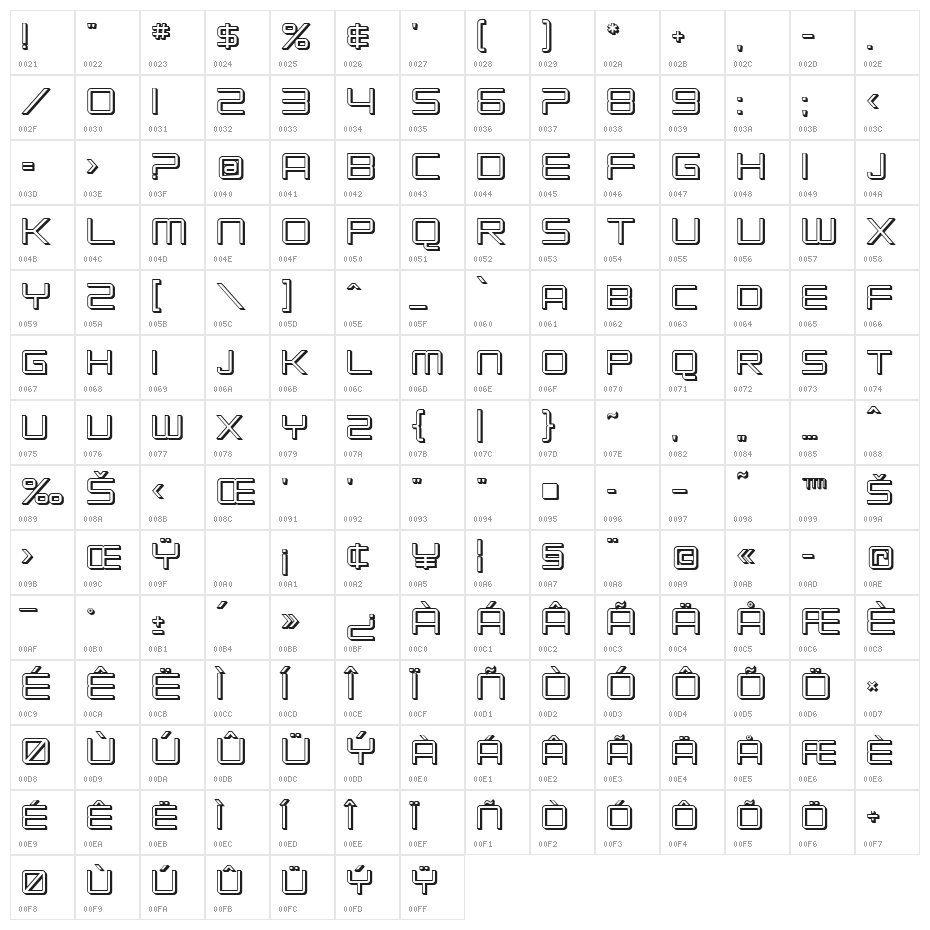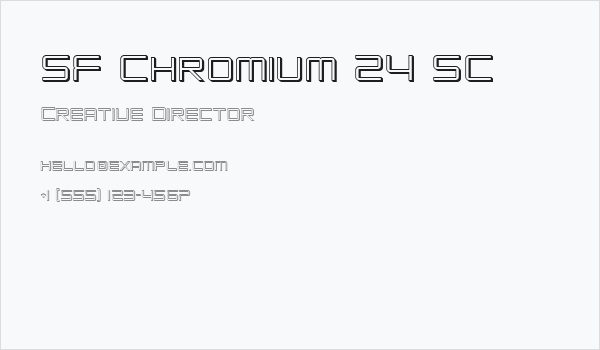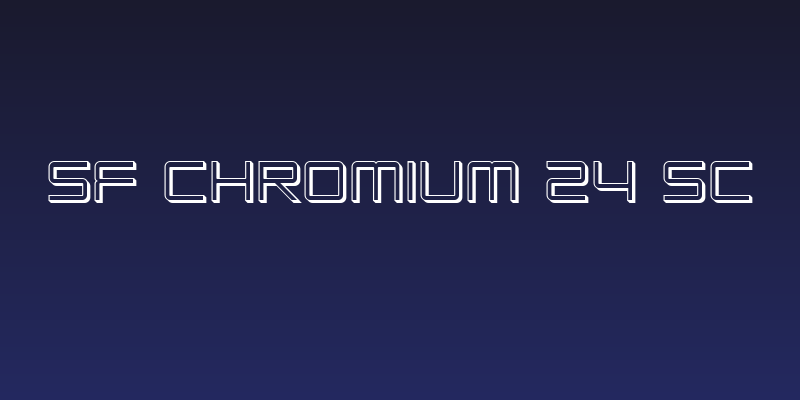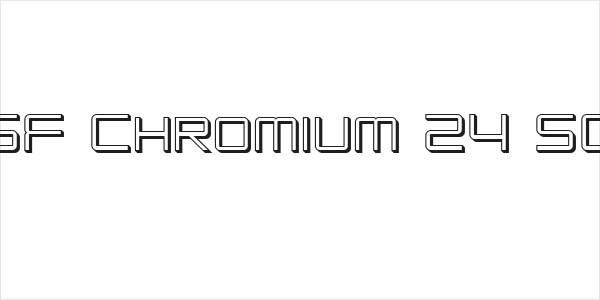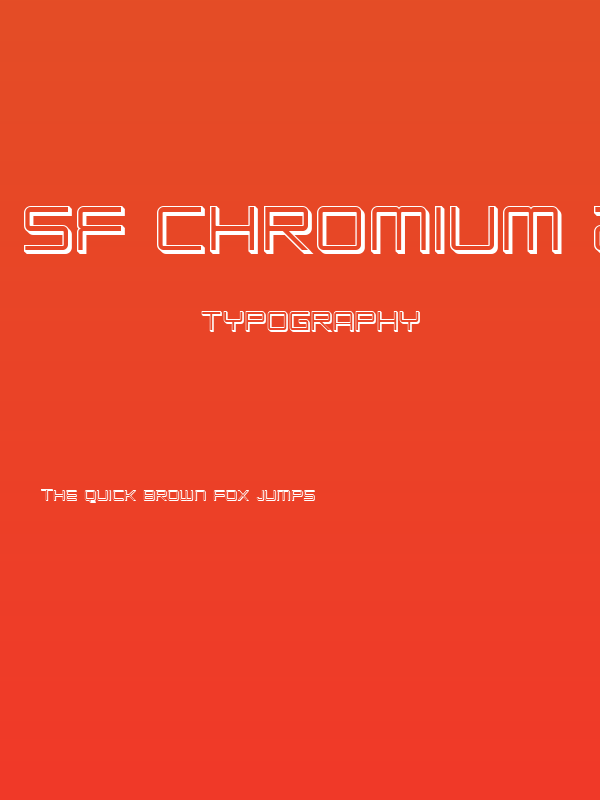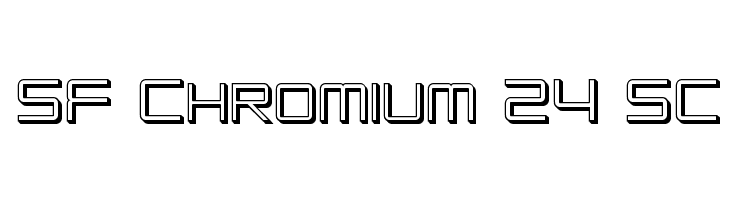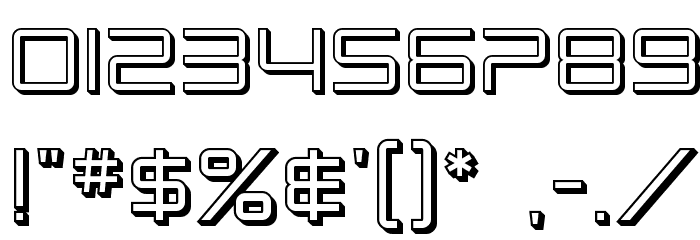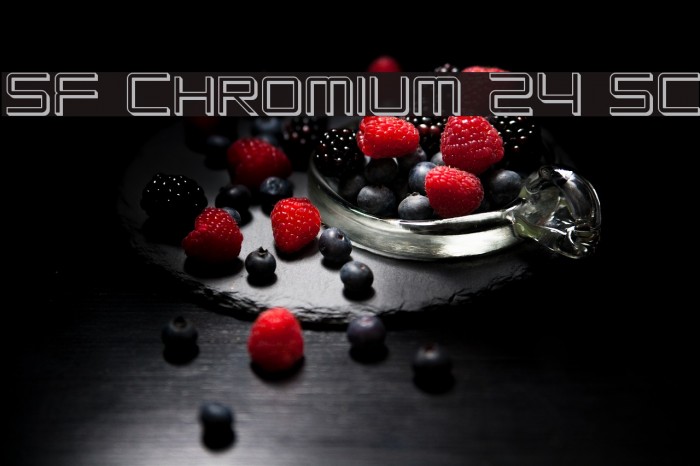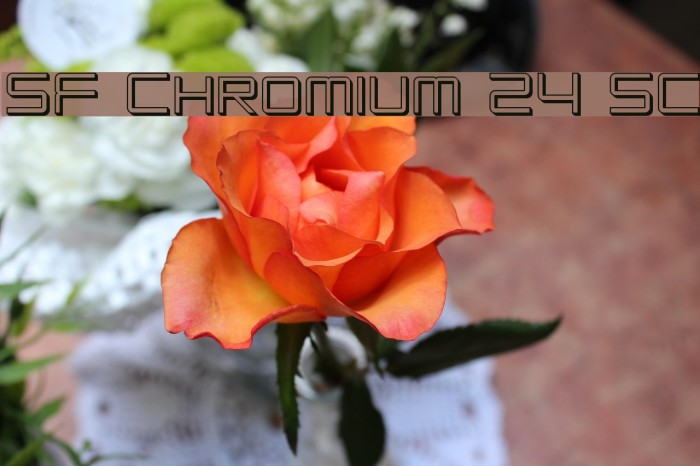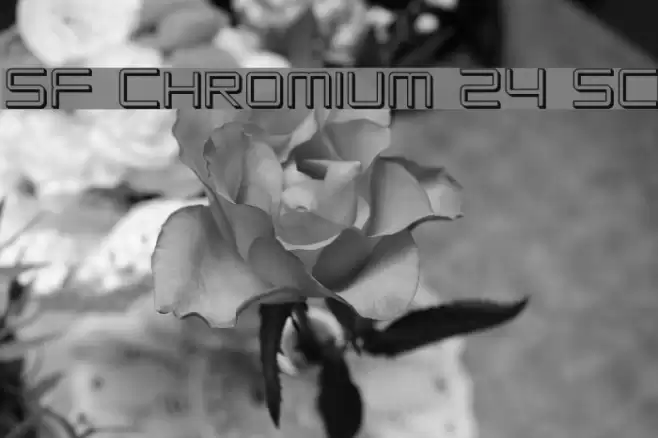
SF Chromium 24 SC Font
| おすすめプロジェクト | Ideal for technology branding, sci-fi themed designs, video game interfaces, and modern advertising campaigns. |